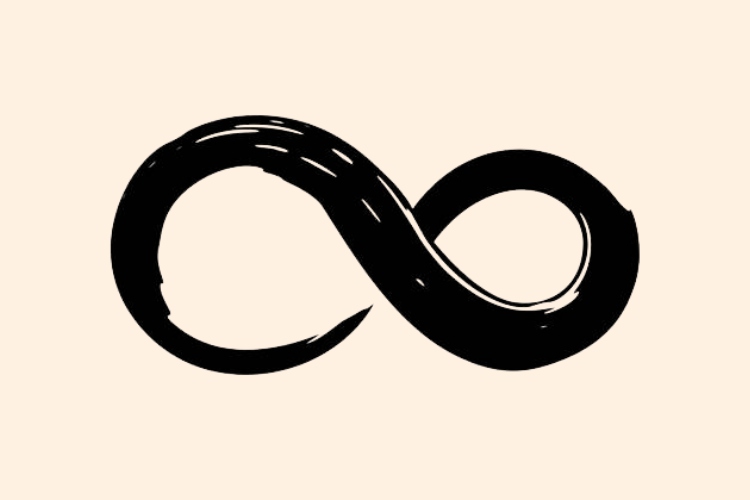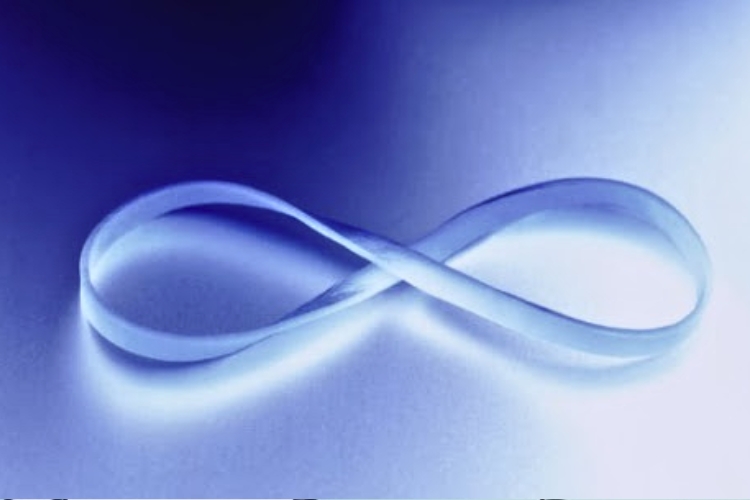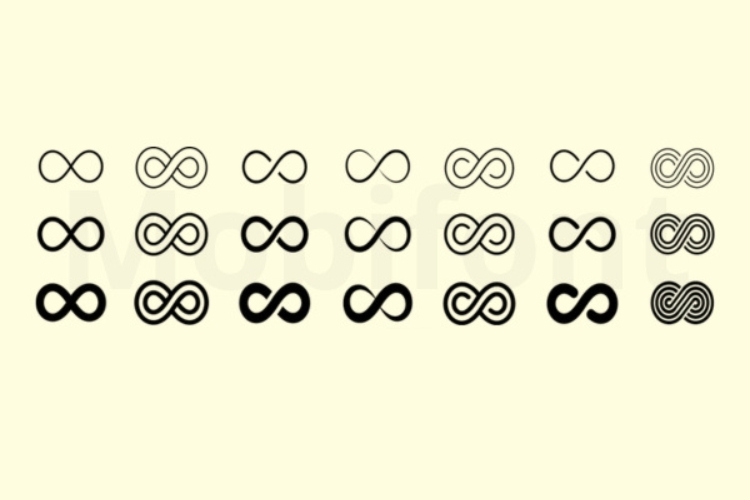
100+ kí tự vô cực đơn giản, có hiệu ứng, kết hợp chữ siêu đẹp, mang phong cách ngẫu nhiên chất lừ
Kí tự vô cực (∞) là một biểu tượng đặc biệt đại diện cho sự vĩnh hằng, không giới hạn và vô tận. Trong ngôn ngữ ký hiệu, vô cực thường mang ý nghĩa của những điều không có điểm kết thúc – từ tình yêu, thời gian cho đến tiềm năng.
Kí tự vô cực (∞), còn được gọi là vô cực kí hiệu hay kí hiệu vô cùng, mang ý nghĩa tượng trưng cho sự vĩnh hằng, không giới hạn và không có điểm dừng. Hình dạng đặc trưng của biểu tượng này là số 8 nằm ngang. Trong tiếng Latinh, hình dạng này được gọi là "lemniscate", dùng để chỉ các đường cong liên tục không có điểm bắt đầu hay kết thúc.
Theo nhiều nền văn hóa và lĩnh vực, kí tự vô cùng đại diện cho chu kỳ lặp lại, sự liên tục hoặc những giá trị không đo lường được bằng con số cụ thể.
Kí hiệu vô cùng được giới thiệu lần đầu vào năm 1655 bởi nhà toán học người Anh John Wallis. Kể từ đó, biểu tượng này nhanh chóng trở thành một phần quan trọng trong hệ thống ký hiệu toán học hiện đại, dùng để biểu thị khái niệm vô hạn.
Theo thời gian, ý nghĩa của biểu tượng vô cực đã vượt ra ngoài khuôn khổ toán học. Trong các lĩnh vực như triết học, tôn giáo và nghệ thuật, kí tự đặc biệt vô cực được sử dụng để đại diện cho những khái niệm sâu sắc hơn như vũ trụ vô tận, tình yêu vĩnh cửu hoặc những chu kỳ bất tận của cuộc sống. Chính vì vậy, biểu tượng này không chỉ mang tính học thuật mà còn trở thành một hình ảnh phổ biến trong văn hóa đại chúng, thời trang và nghệ thuật đương đại.
Những kí tự đặc biệt hình vô cực cơ bản và phổ biến thường thích hợp cho các nền tảng hỗ trợ ký tự Unicode tiêu chuẩn. Theo Unicode Consortium, phần lớn các biểu tượng này nằm trong khối Mathematical Operators (U+2200-U+22FF), Miscellaneous Symbols (U+2600-U+26FF), Miscellaneous Mathematical Symbols-B (U+2980-U+29FF), Vai Syllabary (U+A500-U+A63F),...
Bảng dưới đây gợi ý một số ký hiệu đơn giản mà bạn có thể tham khảo:
Biểu tượng |
Tên Unicode |
Mã Unicode |
Mô tả ngắn |
∞ |
Infinity |
U+221E |
Biểu tượng vô cực cổ điển, thường dùng trong toán học |
ꝏ |
Latin Letter Infinito |
U+A74F |
Chữ Latin cổ dùng thay thế cho biểu tượng vô cực |
♾ |
Permanent Paper Sign |
U+267E |
Biểu tượng giấy lâu bền, giống hình vô cực trong vòng tròn |
⧞ |
Circled Crossing Lanes |
U+29DE |
Biểu tượng giao nhau vòng tròn, hình dạng vô tận |
⧜ |
Left Fish Tail |
U+29DC |
Đuôi cá bên trái, hình trang trí uốn cong |
⧝ |
Right Fish Tail |
U+29DD |
Đuôi cá bên phải, hình đối xứng đuôi trái |
Ꝏ |
Latin Capital Letter Omega With Loop |
U+A74E |
Biến thể chữ cái Omega với vòng lặp |
꘎ |
Vai Syllable Oe |
U+A60E |
Ký tự âm tiết trong chữ viết Vai, hình vòng lặp độc đáo |
ꚙ |
Cyrillic Capital Letter Omega With Titlo |
U+A699 |
Chữ cái Kirin cổ với dấu Titlo, hình cong |
∽ |
Sine Wave |
U+223D |
Sóng sin, biểu tượng toán học cho sự dao động, vô hạn |
Ngoài ra, dưới đây là một số tổ hợp kí tự cơ bản dành cho bạn:
∽̅
∞̅
∞̶
∞̷
∞̲
∞̴
∞͓
∞͜∞
Các kí tự vô cực được thiết kế với hiệu ứng tô điểm như viền, bóng mờ, gạch chân hoặc kết hợp hiệu ứng Unicode, thường dùng để tạo điểm nhấn nổi bật trong tên hiển thị và mô tả ngắn gọn. Tham khảo các icon vô cực có hiệu ứng đẹp sau đây:
∞⃝
∞͜∞
∞✧
∞❥
∞͓̽
∞̾
∞⃞
∞⃠
∞҉
∞͟∞
∞҂
∞⸙
∞✩
∞☆
Nhóm kí tự kết hợp giữa biểu tượng vô cực với chữ cái, kí hiệu cảm xúc hoặc các icon trang trí giúp tạo ra tên gọi và tiểu sử độc đáo. Dưới đây là một vài ví dụ cụ thể về kí hiệu vô cực kết hợp giữa chữ cái và biểu tượng siêu ấn tượng:
꧁∞Lᴏᴠᴇ∞꧂
❥∞𝓢𝓱𝓲𝓷𝓮∞
∞𝐌𝐘𝐒𝐓𝐈𝐂∞
𝓣𝓲𝓶𝓮∞𝓛𝓮𝓼𝓼
꧁༒∞Pᴀɪɴ∞༒꧂
♾️Sᴏᴜʟ∞Vɪʙᴇ♾️
∞🅛🅞🅥🅔∞
∞❤️𝓣𝓻𝓾𝓮𝓛𝓸𝓿𝓮❤️∞
☆彡∞𝓗𝓮𝓪𝓻𝓽𝓑𝓮𝓪𝓽∞彡☆
☾∞DʀᴇᴀᴍCʜᴀsᴇʀ∞☽
∞𝔇𝔞𝔯𝔨ℜ𝔦𝔰𝔢∞
∞༆ᗰι𝓁𝓀𝓎𝕎𝕒𝕪༆∞
Những kiểu chữ vô cực mang phong cách cá tính, bay bổng và đầy nghệ thuật là lựa chọn hoàn hảo để bạn đặt tên hiển thị thật nổi bật. Danh sách một số kiểu chữ cực đẹp và chất như sau:
౨ৎʋôɕựɕ🎀
ᰔᩚvôςựς▁⌇
ᓚᘏᗢ౮ô८ự८ᘛ⁐̤ᕐᐷ
hဗီူᐯôᑕựᑕ˚༘ೀ。
mʚရှီɞ🆅ô🅲ự🅲ᝰ.ᐟ
၄၃vôcực౨ৎ
જ⁀➴νôςựς♡
(‿ˠ‿)ѵôɕựɕ
2√ôɔựɔⱭ͞ ̶͞ ̶͞ ̶͞ لں͞
꧁༒ʋô•ͼựͼ༒꧂
ミ★vôcực★彡
ᥫᩣvôcựcㅤूाीू
´꒳`ⓋôⒸựⒸ×͜×
—̳͟͞͞♥ҩôℭựℭ
亗✔ô☾ự☾ෆ
ϟṿôϟċựċ⚡︎
♰V̆ô♰C̆ựC̆♰
ʌôɔựɔ☃︎
ദ്ദി ˉ͈̀꒳ˉ͈́ )✧ѵôçựç
Những mẫu tên dưới đây là sự kết hợp tự do giữa kí tự vô cực, biểu tượng đặc biệt và font chữ phá cách, giúp tạo ra hiệu ứng bất ngờ và thu hút:
❤νô╰‿╯(ự©❤
☂√̝ô☯ᑕực͎๛